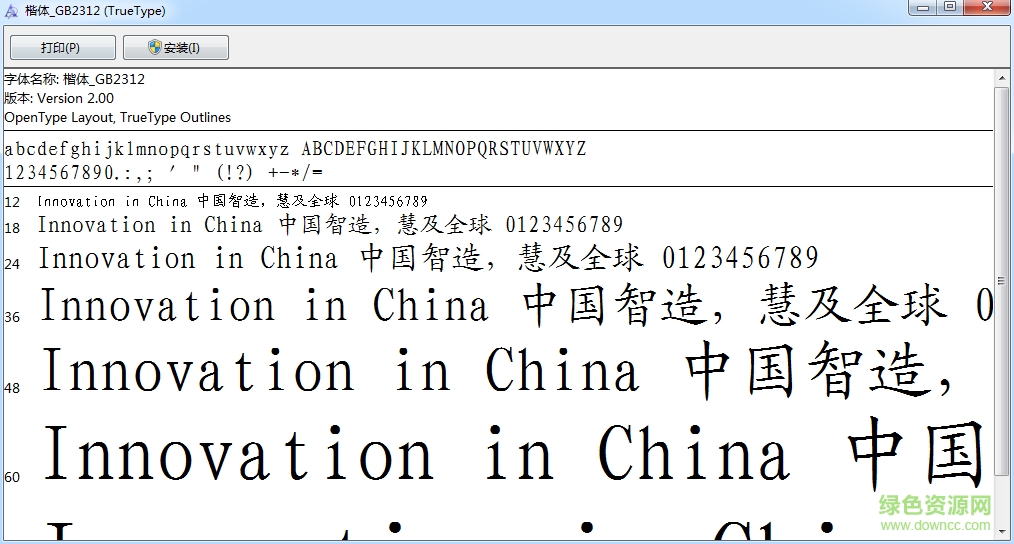
楷體普通西方字體是一款非常實用的常規(guī)字體,結構規(guī)整,一撇一捺都十分規(guī)范,適合文字印刷、雜志期刊、平面設計等各個方面,大方得體,有需要者歡迎免費下載!
1~3厘米的為小楷(小字),5厘米以上的為大楷(大字),之間的為中楷。但這僅僅是籠統(tǒng)的分法,實際上,現(xiàn)實生活里很少出現(xiàn)過小于1厘米的小字和大到1.8米的大字。
如今一般所說的楷書,是從漢隸逐漸演變而來的,按照時期劃分,可分為魏碑和唐楷。魏碑是指魏、晉、南北朝時期的書體,它可以說是一種從隸書到楷書的過渡書體!